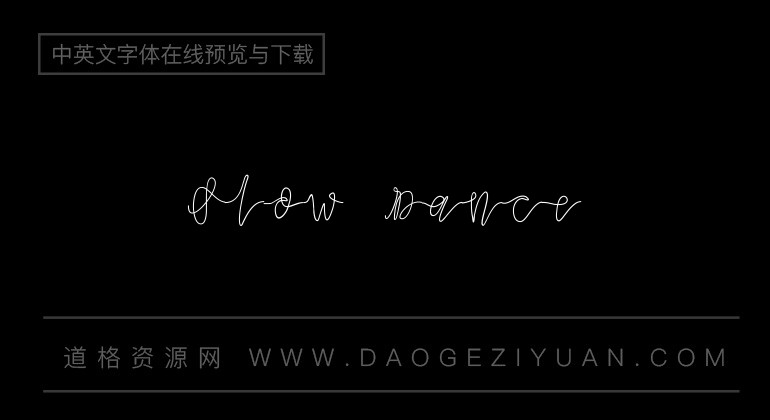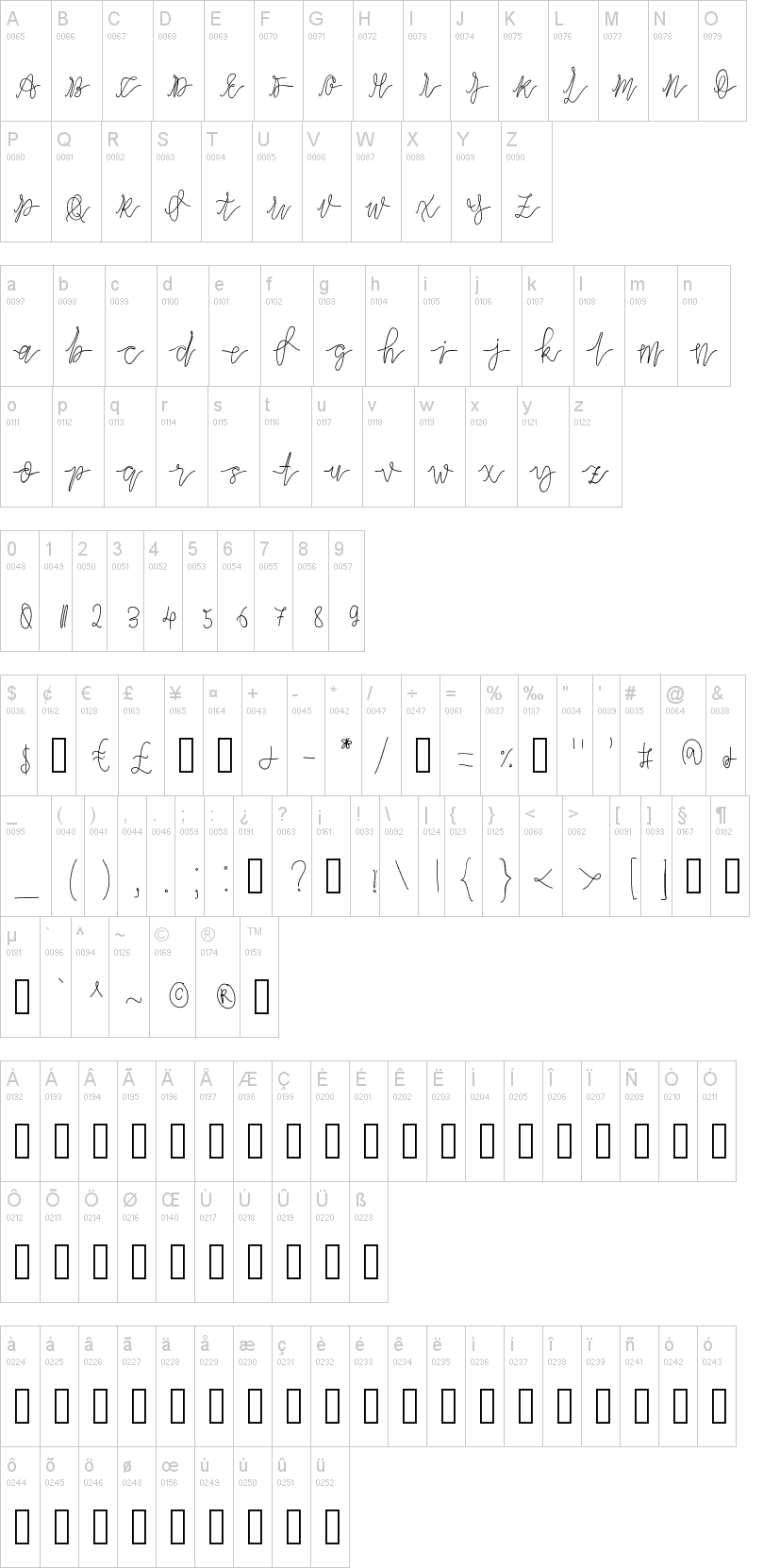
Slow Dance 是一款由 Typodermic Fonts 出品的一款字体,它是一款拥有细节丰富的古典风格字体,它可以用于创建浪漫的氛围,也可以用于表达古典的气息。它可以帮助您在设计中创造出优雅和精致的文字效果。它有多种字体粗细和字形,可以满足您的不同需求。内容介绍
Slow Dance是一款非常不错的手写艺术字体,具有很好的视觉感,适合于文化类的宣传设计、商业类品牌的广告和产品包装设计以及个性化文字排版等较多场景。